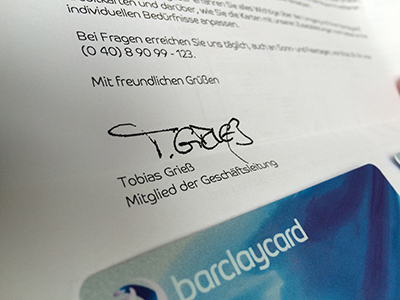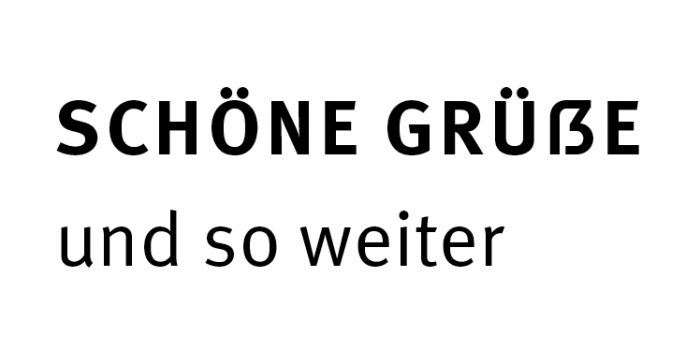
Kleiner Nachtrag:
Die "Trajan 3" ist eine Versalschrift und beinhaltet daher kein kleines "ß".
Das trifft aber nur auf Schreibprogramme zu (z. B. Word).
Layoutprogramme mit OT-Unterstützung ersetzen "ß" durch Doppel-s.
Aber nur dann, wenn das die OpenType-Daten des Fonts bei der Auswahl "Kapitälchen" so vorgeben. Ist in den Kapitälchen, die ja praktisch ein zweiter Satz Gemeine in alternativer Darstellung sind, dann auch ein Kapiitälchen-ẞ enthalten, dann wird das auch gesetzt.
Du hast natürlich recht, dass die Möglichkeit besteht, dies im Font so einzustellen.
Aber selbst Schriften, die ein Versal-SZ und ein Kapitälchen-SZ beinhalten, ersetzen standardmäßig das kleine“ß“ durch Doppel-s. Der Schriftgestalter kann ja nicht wissen, ob die Anwender ein Versal-SZ bevorzugen.
Man könnte jedoch das Kapitälchen-SZ auf einen Formatsatz legen.
Liebe Kollegen, lasst Ihr mir den folgenden Notbehelf durchgehen?*
Das ist das ẞ der Museo Sans, welches ich in die Meta transplantiert habe. Ich muss nämlich gerade Namen versal setzen und ich bringe es einfach nicht übers Herz, das Eszett in ein Doppel-S zu übersetzen. Meta ist als Hausschrift gesetzt und ich brauche lediglich für den raren Einsatz in versal gesetzten Namen eine ẞ-Lösung. Wenn ich mal mehr Zeit habe, werde ich mich der Erstellung eines Ein-Zeichen-Fonts widmen und mir für diesen Zweck ein Versal-Eszett selber zeichnen, aber jetzt habe ich dafür zu viel Zeitdruck. Vielleicht erhört ja in der Zwischenzeit auch der legendäre Metaman™ mein Flehen und zaubert ein ẞ?
* Es ist einen Hauch zu dünn und natürlich müsste ein richtiges ẞ auch eine etwas andere Form haben … Aber für den Notfall? Oder fällt Euch eine bessere Hilfsvariante ein?
Stimmt. Mein Text ist zum Glück in echt nur in 9 Punkt gesetzt, da ist das nicht sooo dramatisch. Fällt Dir sonst jetzt auf die Schnelle ein besser geeignetes, existierendes Versal-Eszett ein? Vielleicht setze ich mich sonst am Wochenende doch noch dran und baue eins, obwohl ich da eigentlich tausend andere Dinge tun muss …
Das Programm habe ich ja bereits – aber im Moment leider überhaupt keine Zeit, mich da reinzufuchsen. Sonst gibt’s für mich gar keinen Nachtschlaf mehr …  ;-)
Ich finde es interessant, dass in diesen Videos im Gemischtsatz anscheinend bewusst das (vermeintlich schülerfreundlichere) einstöckige a verwendet wird, denselben (an Nachhilfe interessierten!) Schülern aber andererseits schon zugetraut wird, das versale zu erkennen. Soweit sind wir also schon! :biglove:
Das hamm’ wir jetzt davon … #versaleszett #scheißegal DIE SÜßE GIER #film #plakat http://instagram.com/p/xoxqiMIckL/
Umso mehr kommt es wohl darauf an, dass die »richtige« Form kommuniziert wird. Ich würde das aber nicht als Gegenargument sehen. Was meint Ihr?
ich zitiere mal:
>AUA. Das tut ja im Auge weh!
>Liebe Deutsche, macht es wie die Schweizer und schafft das esszett ab. Dann gibt's diese Probleme nicht mehr.
>scheint gerade irgendwie hip zu sein ... ich versteh's auch nicht.
>Buchstabenvergewaltigung
>Ist nicht hip. Es gibt Leute die wollen auf biegen und brechen ein Gross-eszett einfuehren. Das wurde auch beim Unicode durchgestiert, damit bei Kapitalisierung das eszett nicht zerfaellt.
>Ja das ist ein Versal-ß und ich finde es gut. Das ß wie wir es kennen entstand als Ligatur in gebrochenen Schriften, die aber niemals rein Versal gesetzt wurden (Manche Rocker und Nazivereine wissen das zwar nicht und setzen trotzdem ihr Vereinslogo aus Versalen Gotischen Buchstaben, das Ergebnis ist visueller Brechreiz). Mit Lateinischer Schrift funktioniert das aber wunderbar so kann man also auch z.B. "GROẞ" schreiben. Weil es kein Versal-ß gegeben hat (warum auch immer/es gab Reformversuche/der Duden hatte in einigen Ausgaben ein Solches auf der Front), hat man sich mit der Rechtschreibregel: "GROSS" beholfen. Funktioniert wunderprächtig, ist aber eigentlich umständlich, naja man hat sich halt dran gewöhnt. Ich weiß nicht warum sich alle beim Thema Versal-ß so einscheißen. Das Teil ist das Ergebnis konsequenter Typografie und kritischer Überlegung. Vorallem ist es das Ergebnis zahlreicher Experimente, es ist historisch belegt, stammt aus der Feder eines Zeichenexperten und löst kleinere Rechtschreibverwirrungen auf. Kein Mensch braucht es, außer die, die es schätzen. Na und? Ich trinke gerne Energy-Drink. Kein Mensch außer mir mag das Zeug einfach so, trotzdem lass ich mir das nicht verbieten. In diesem Sinne: Guten Appetit.
>es geht hier auch nicht um die diskussion versal eszett ja oder nein sondern einfach darum das dieses eszett einfach unschön aussieht im zusammenspiel mit den umgebenden buchstaben (weißräume) und nicht so eigenständig ist, das man es nicht für ein B halten könnte
>Jetzt mal ehrlich. Strabe geht gar nicht. Was sollen denn unsere Kinder von uns denken.
... alles kommentare zu genau diesem bild.
... Kapitalisierung ...
Das sagt man aber doch nicht wirklich zu Versalsatz, oder?!
Hört sich eher nach BWL-Sprech an ...
Eine Kapitalisierung des ẞ währe, wenn es gesetzlich vorgeschrieben würde, und man als einzigere eine Schriftgießerei betreibt, und alle, die noch mit Blei drucken dann mit ẞ-Lettern beliefern dürfte.
Mark Simonson über seine Proxima Nova:
Capital eszett, (ẞ). Some German speakers think this is a stupid idea, some think it is long overdue. It’s there if you want it.